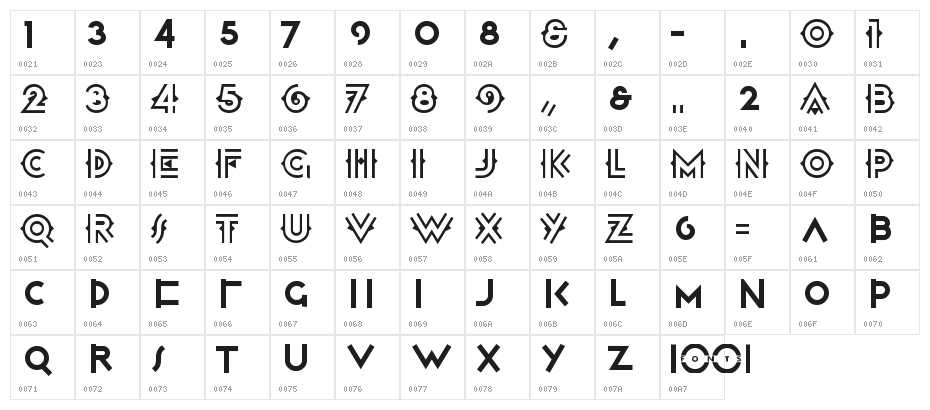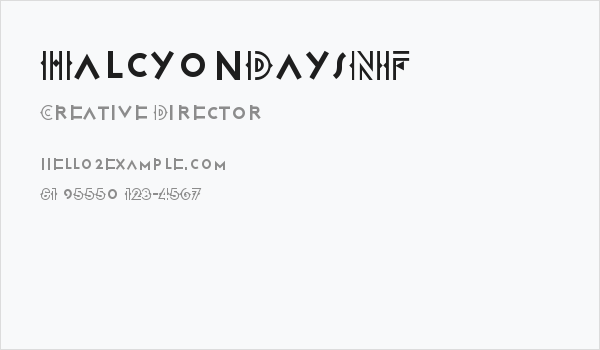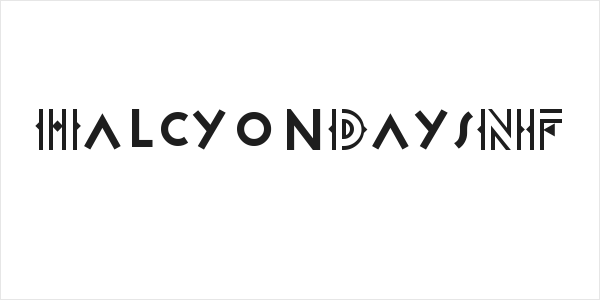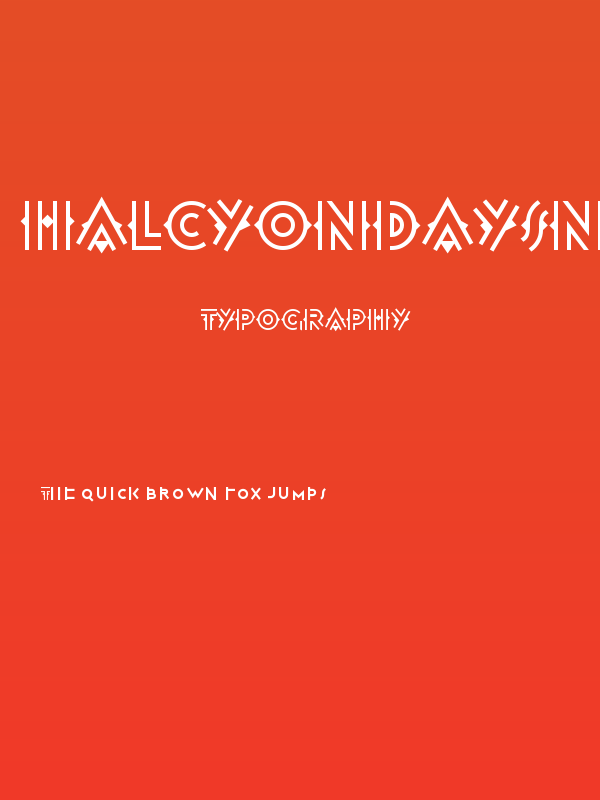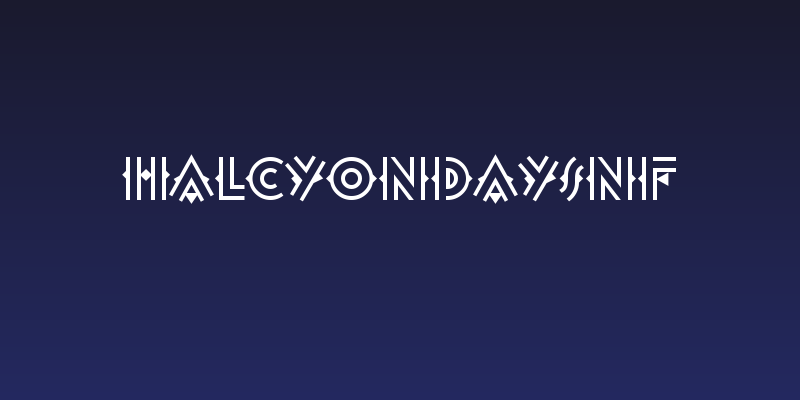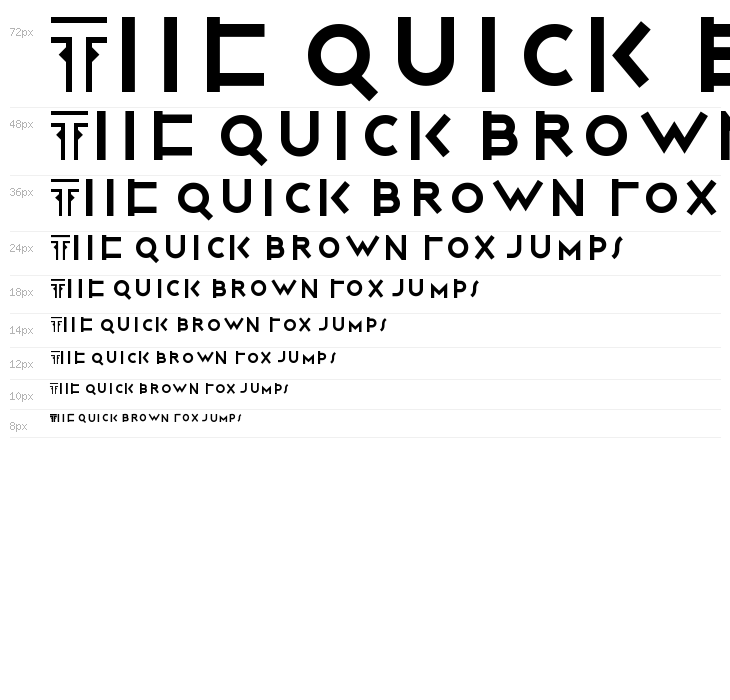
HalcyonDaysNF Font
✎ Art Deco
| النمط العام | Vintage |
| مشاريع مقترحة | This font is perfect for projects that require a vintage or retro feel, such as posters, branding, and packaging. It can also be used effectively in headlines and titles to draw attention. |